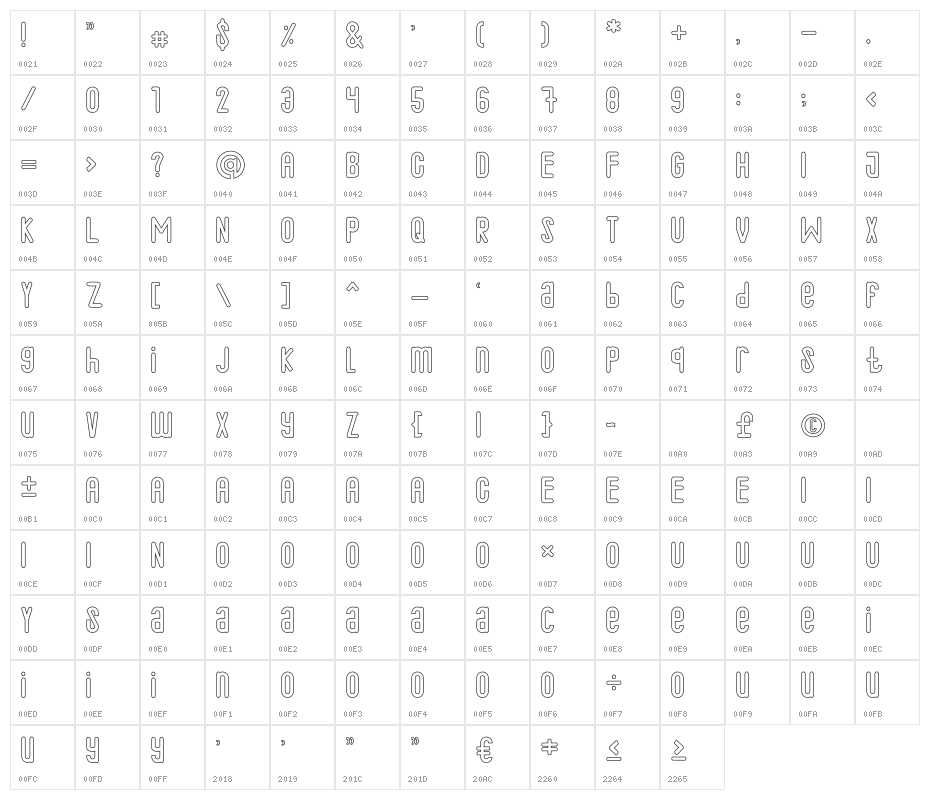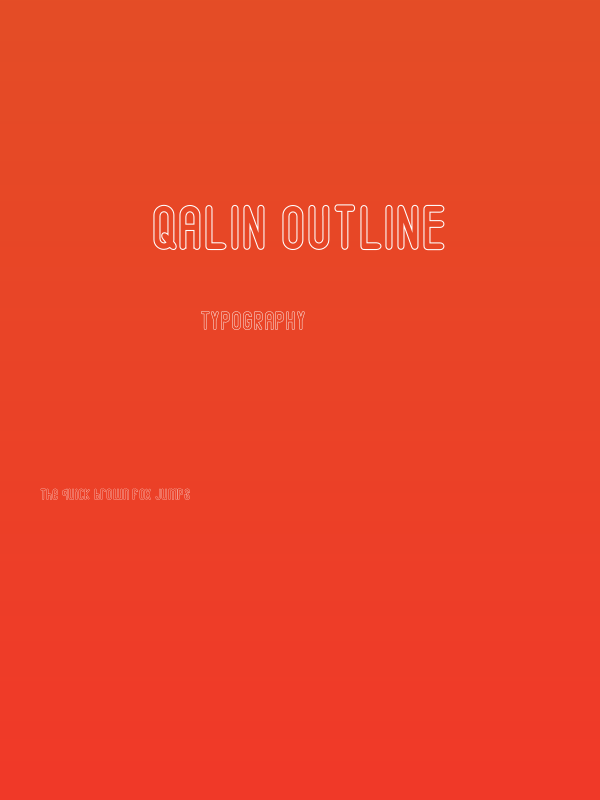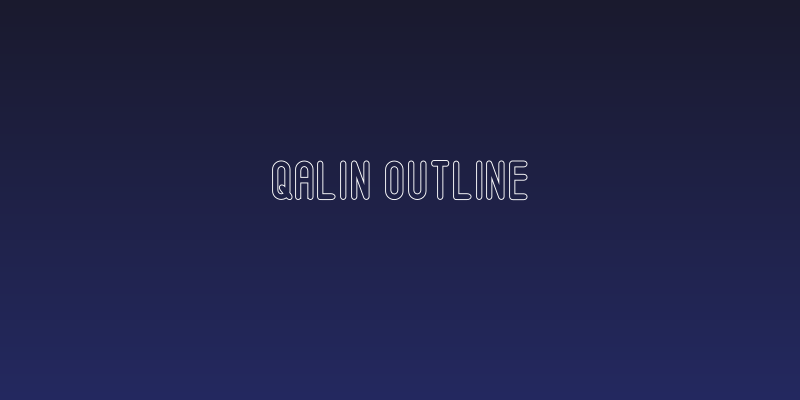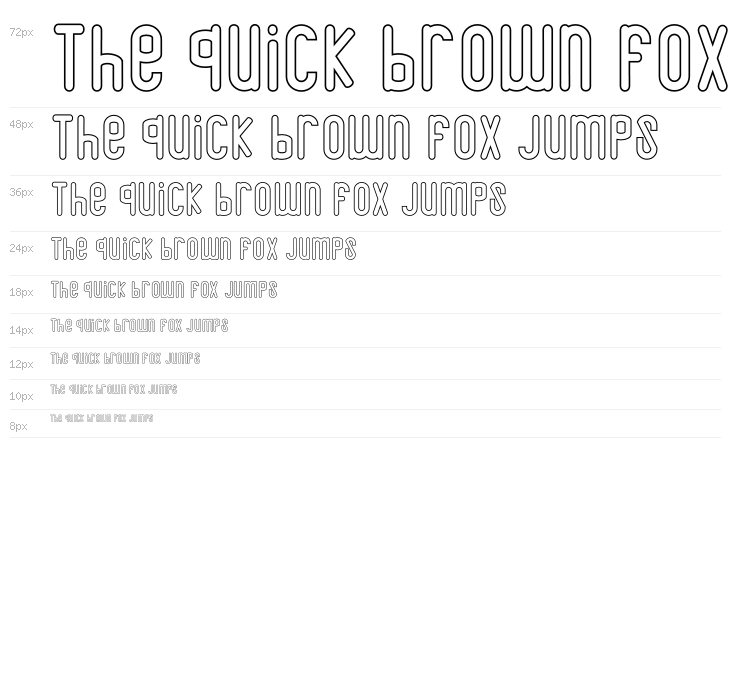
Qalin Outline Font
| Vorgeschlagene Projekte | Ideal for branding, posters, headlines, and digital media where a modern and stylish appearance is desired. |
Qalin Outline